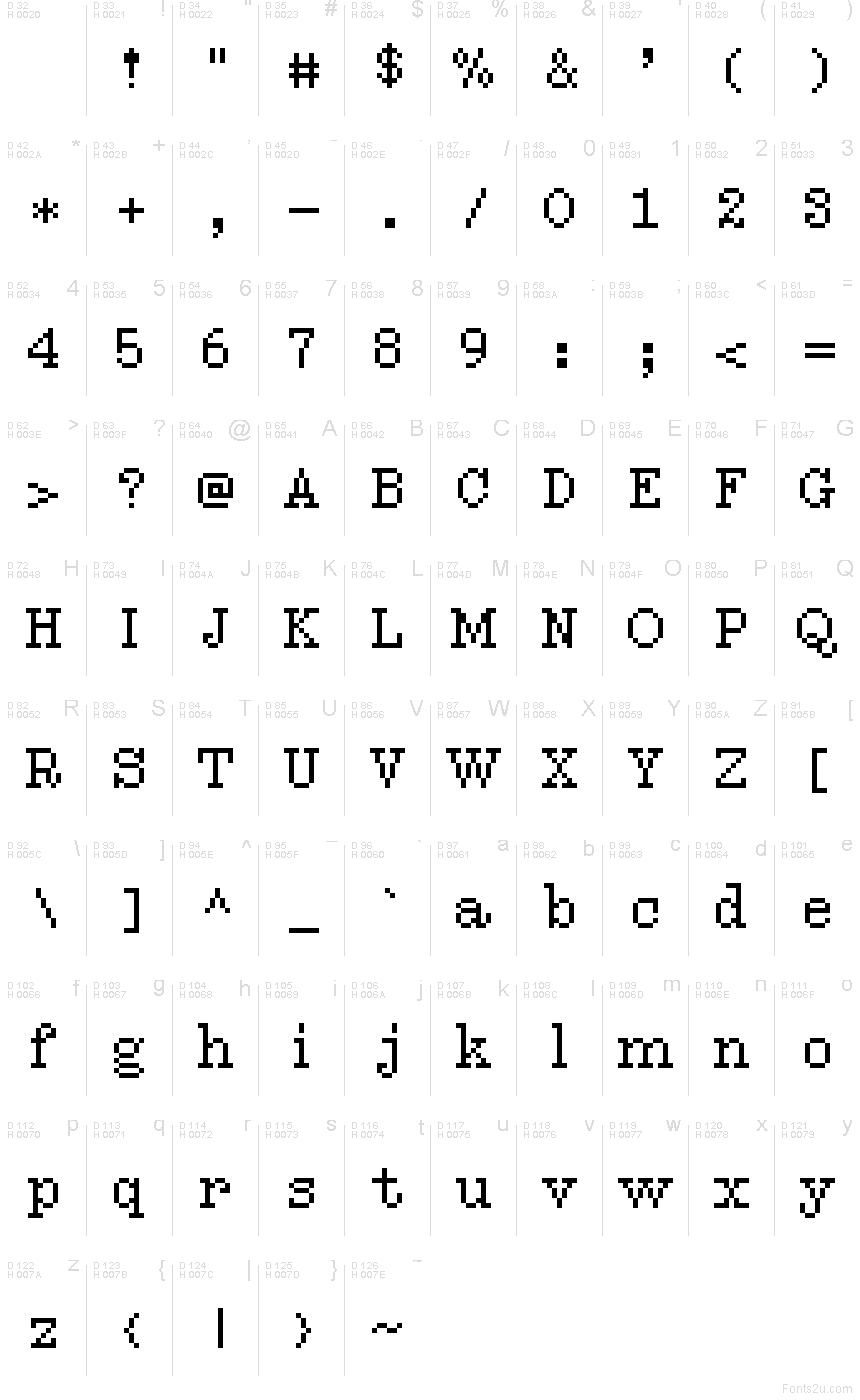
Reindeer Modern od MagicBear je bezplatné pixelové písmo složené z výrazných modulárních tahů a ostře odstupňovaných křivek. Jeho čtvercové tvary mají kadenci připomínající psací stroj, přičemž otevřené mezery a občasné blokové zářezy dodávají sazbě živou texturu v nízkém rozlišení.
Herní grafika je obzvláště přesvědčivým prostředím, protože robustní konstrukce připomíná rané obrazovkové písmo, aniž by kopírovala standardní arkádový styl. Hodí se také na technologické obaly, hudební plakáty a hravý merch zaměřený na publika, která si libují v záměrně drsném digitálním designu. V brandingu mohou tyto seříznuté rohy a nepravidelné spoje proměnit název produktu v kompaktní pixelový emblem.
Pixel je písmo.
Reindeer Didone, which is based on Reindeer Monospace, which is based on Mouse Typewriter
Reindeer Modern
Designer description: <p>Inspired by 19th century "modern" and Scotch Roman typefaces.</p>